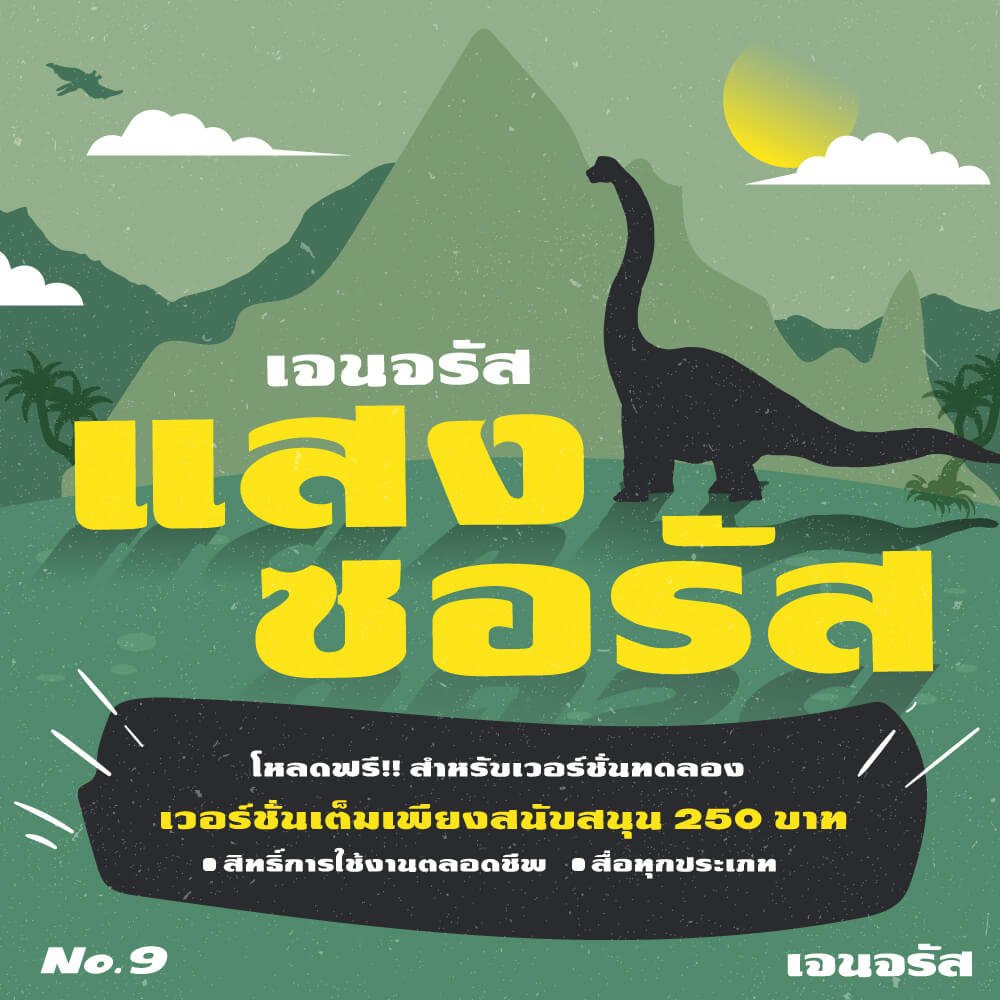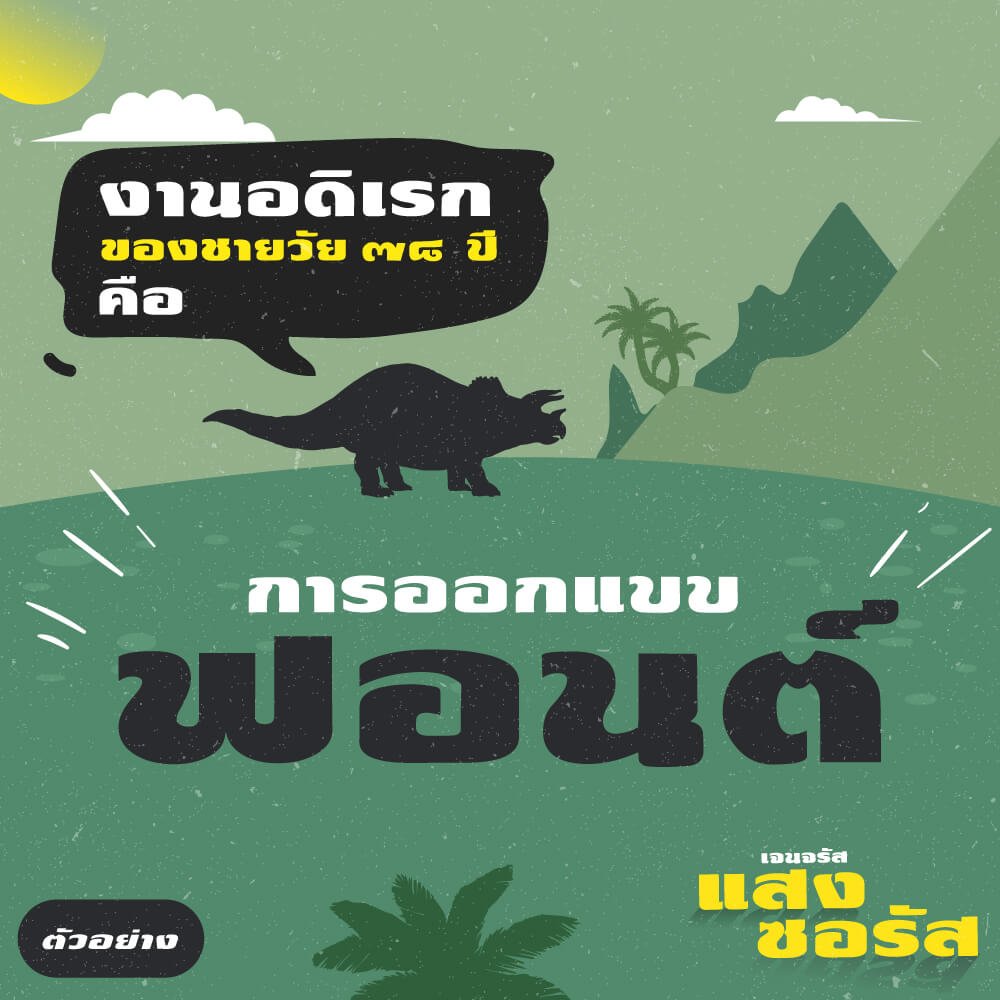
เจนจรัส แสงซอรัส (Jenjrus Saengsaurs)
ฟอนต์เจนจรัส แสงซอรัส เป็นฟอนต์อวบอ้วน หนาๆ คล้ายไดโนเสาร์เต่าล้านปี มีความโค้งมนไม่แข็งทื่อ เหมาะกับเป็นหัวข้อหรือทำป้ายและสื่อโฆษณาต่างๆ
ฟอนต์นี้เป็นผลงาน ชุดที่ 9 ของคุณพ่อ อายุ 78 ปี ที่รักการออกแบบฟอนต์เป็นงานอดิเรกครับ